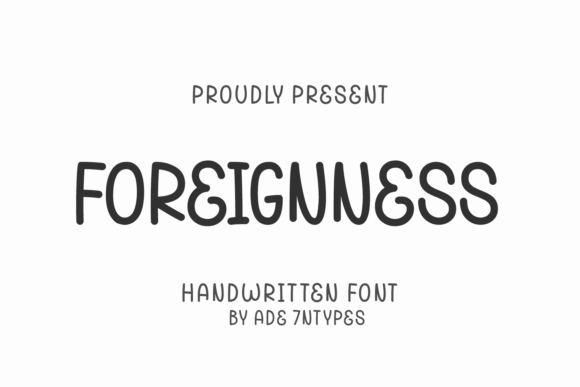
Foreignness
สร้างขึ้นอย่างแม่นยำ Foreignness ให้เวกเตอร์ที่สะอาด พิมพ์ตัวอักษรที่ราบรื่น และใบอนุญาตเชิงพาณิชย์เพื่อความสบายใจ
ไม่ว่าคุณจะสร้างผลิตภัณฑ์ POD (Print on Demand) คำเชิญงานแต่งงาน หรือกราฟิกโซเชียลมีเดีย Foreignness ก็เหมาะสมอย่างยิ่ง